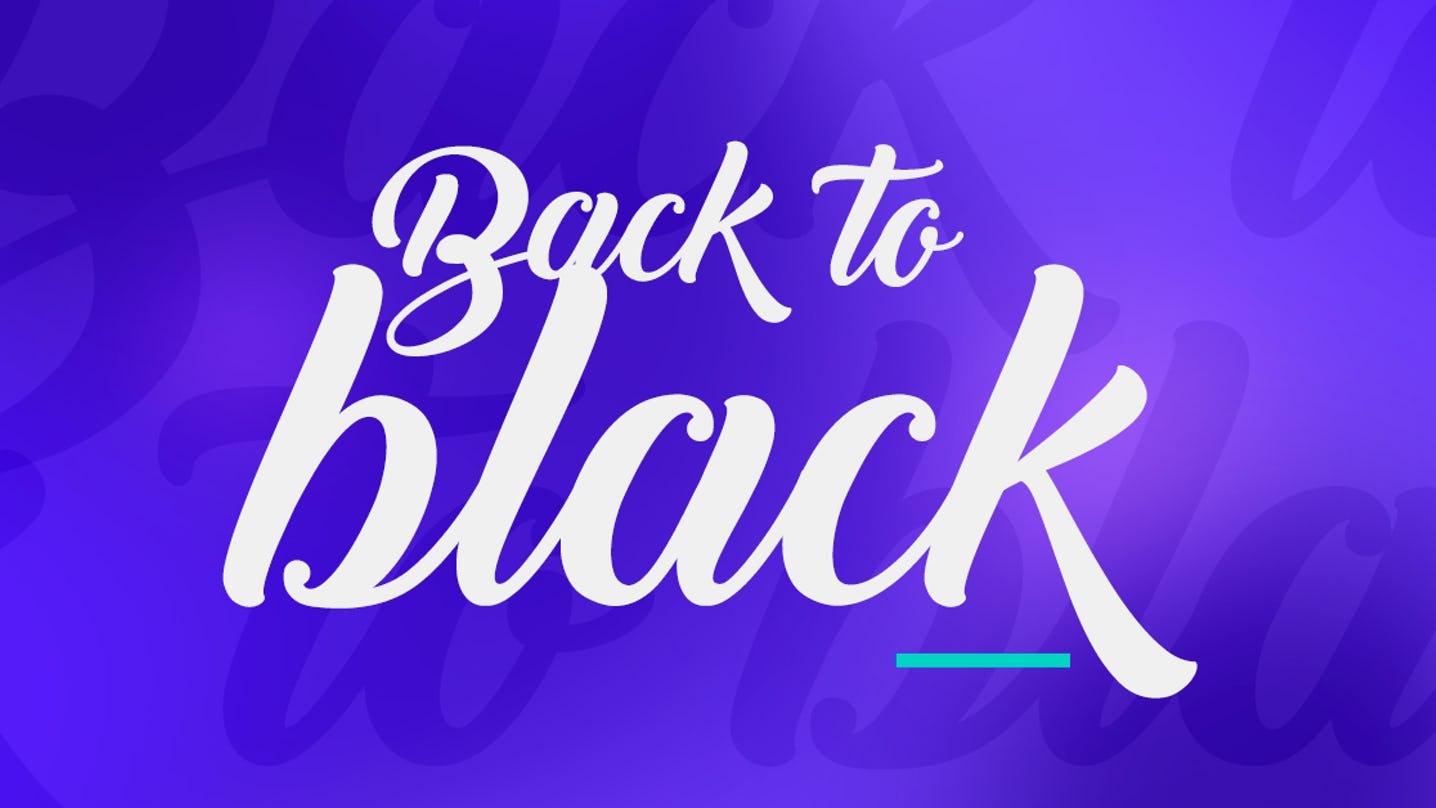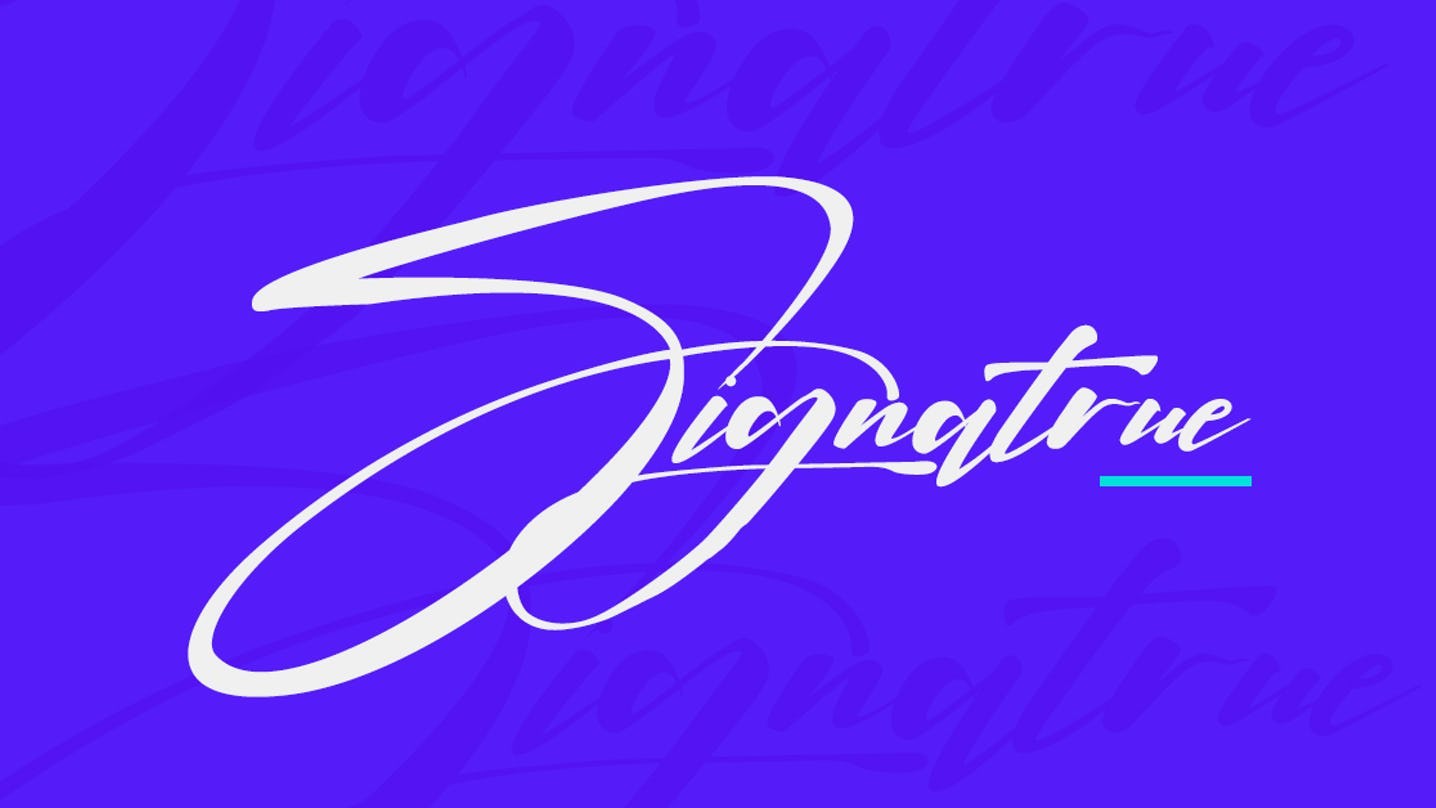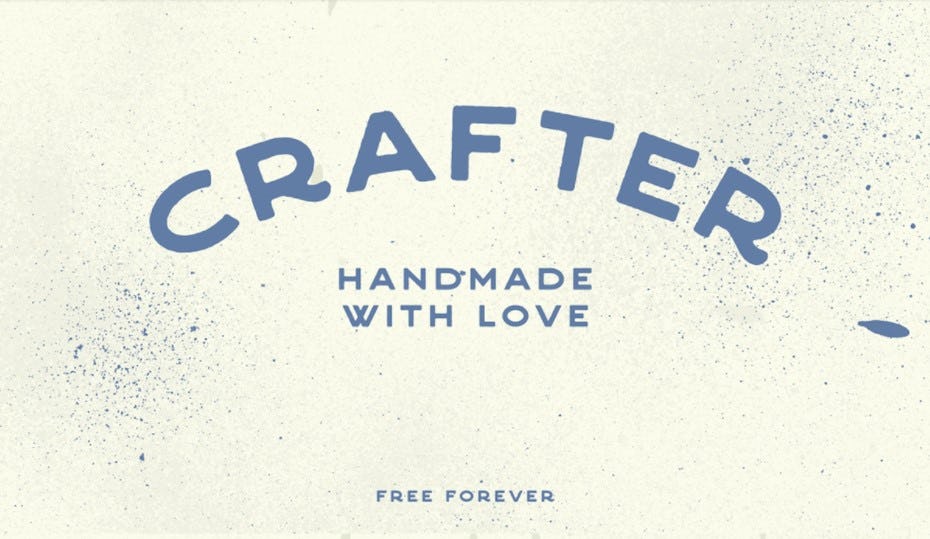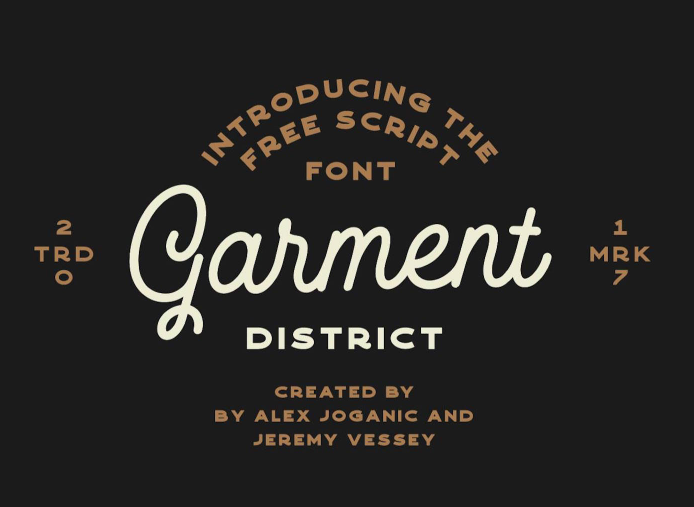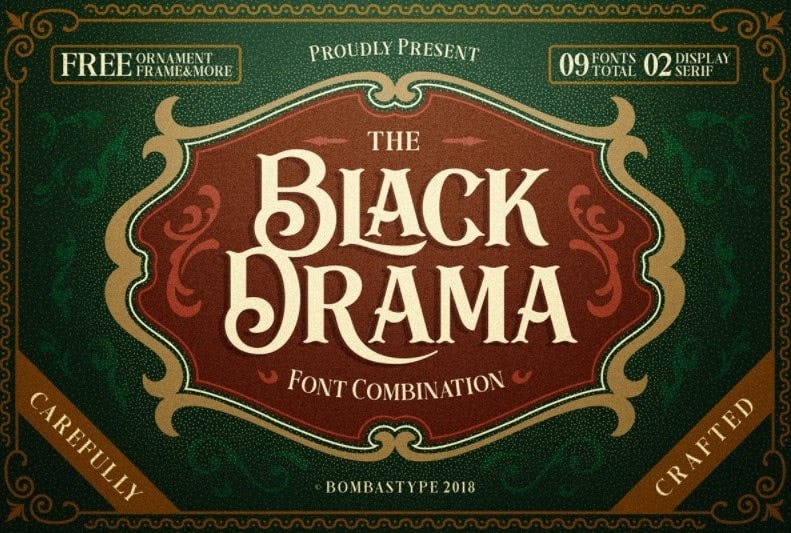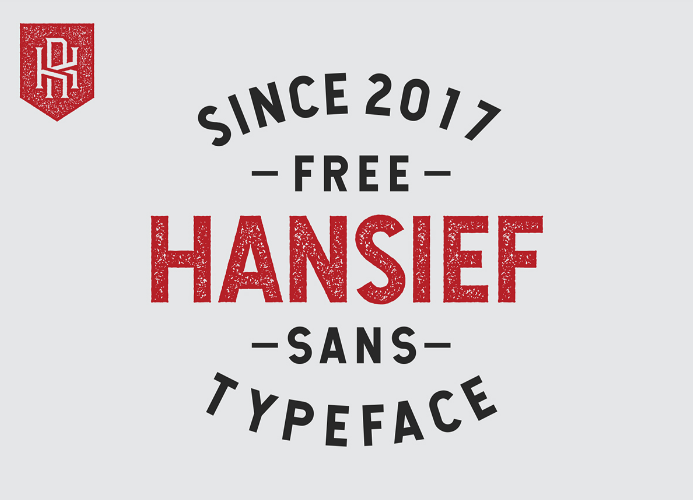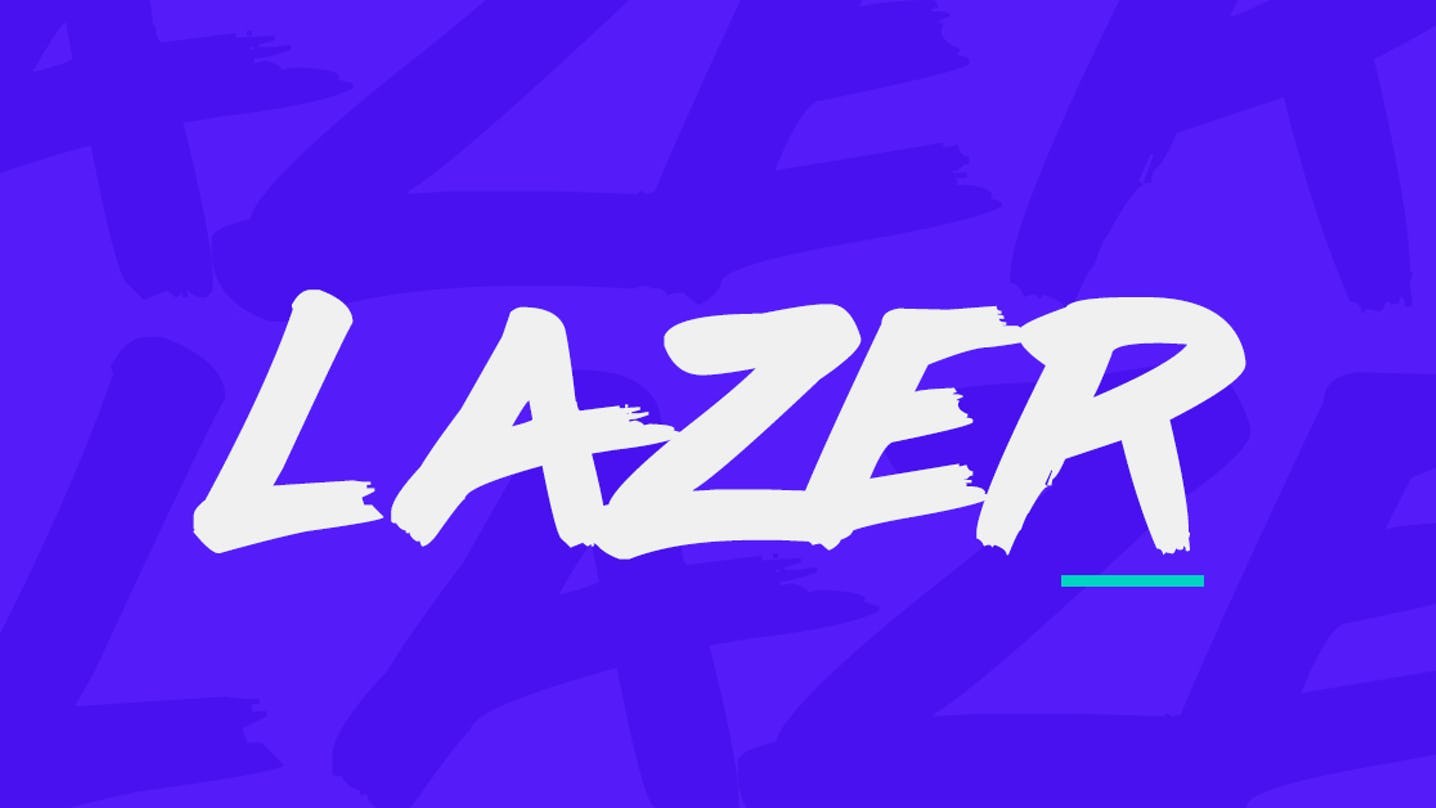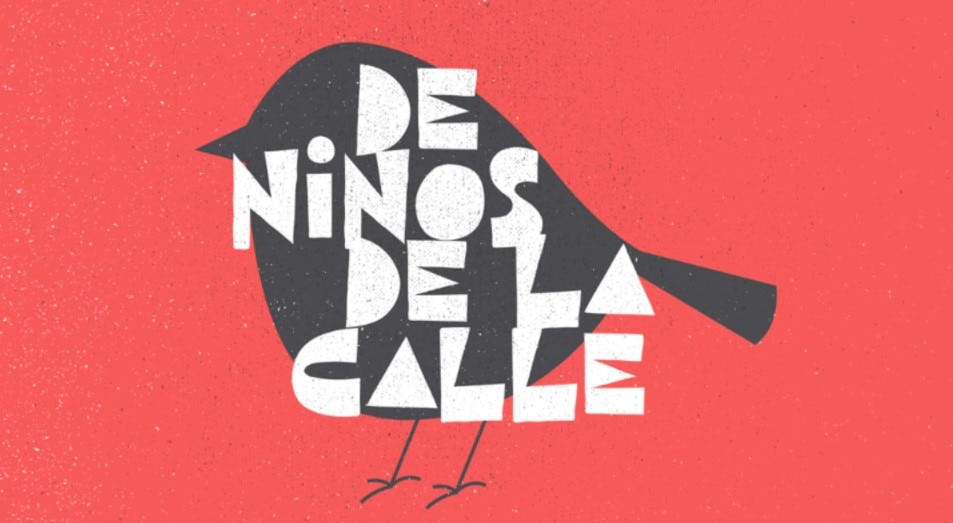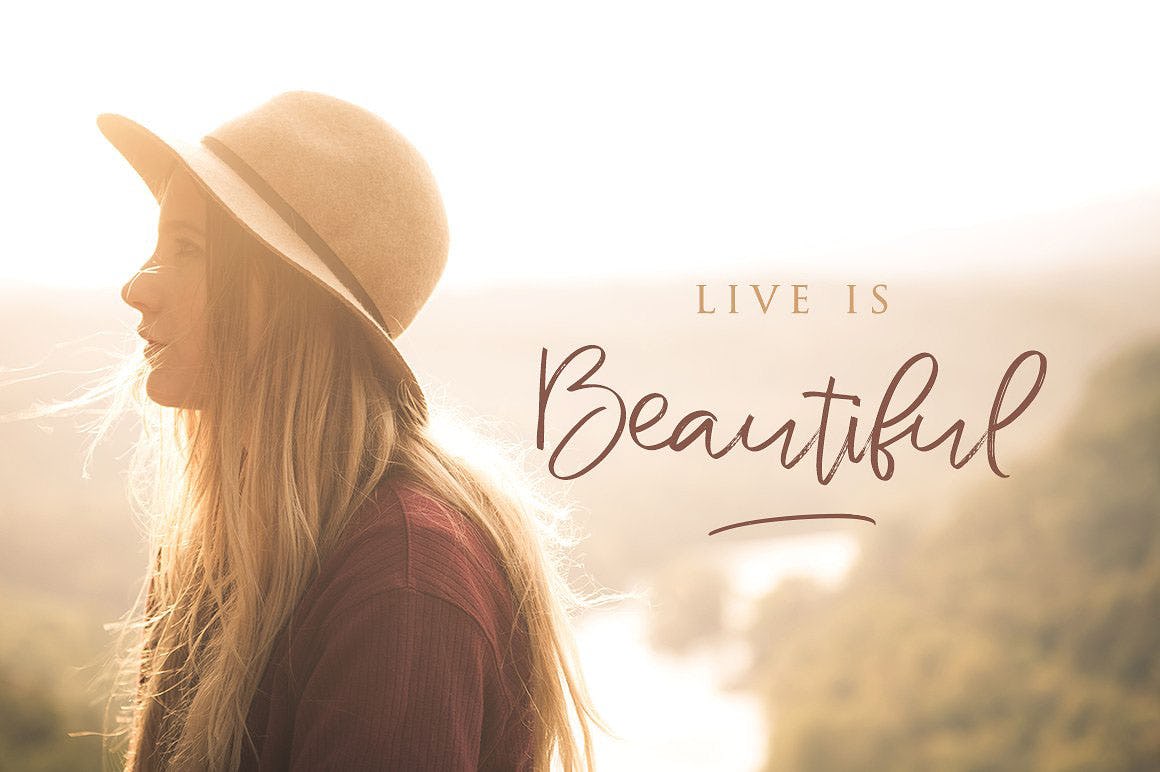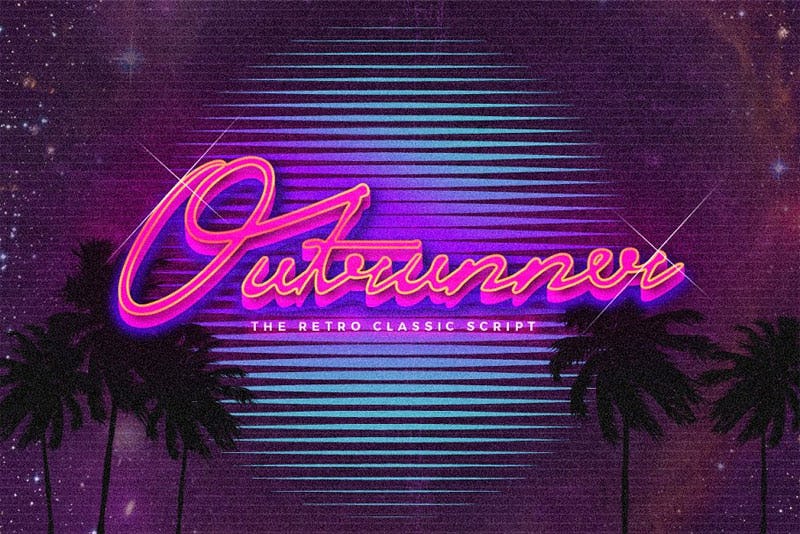
Conhecer o mundo das tipografias vintage é necessário para todo designer gráfico. Por que razão? Porque, ao realizar uma tarefa de design, não são apenas os objetos gráficos e visuais que importam, mas também o formato dos textos que os acompanham. O objetivo é que o espectador que entra em contato com sua peça de design entenda a mensagem que você deseja comunicar num relance. Assim, as tipografias vintage permitem que você gere uma impressão retro na mente do público, comunicando uma mensagem precisa.
Mas quais são as principais tipografias vintage? A que períodos eles se referem? Como podem ser combinados? Não se preocupe, porque em todo este post de Crehana, nós lhe forneceremos um guia informativo completo sobre quais são as melhores tipografias vintage. E como resultado, você terá um ás de estilo vintage na manga como designer profissional.
Streetwear Free Font
Artimasa compartilha conosco a fonte Streetwear, uma fonte vintage e elegante, inspirada na moda e nos esportes dos anos 60 e 70. Esta " velha confiável " é única e divertida ao mesmo tempo, e perfeita para textos, logotipos e frases criativas.
The Night Watch Font
Procurando letras vintage para um projeto com toques clássicos ou medievais? The Night Watch Font é uma fonte vintage gratuita que ajudará você a consolidar os dois estilos. Você pode até usá-lo para evocar o mistério ou para um tema de terror.
Esta é uma fonte retro não convencional com serifs modificados, que chamará a atenção de qualquer material. Utilize-a em ilustrações, cartazes, etc.
Blackletter Font
Se o estilo gótico é o seu estilo, Blackletter Font é o tipo de letra vintage para você. Por ser bold, curvilíneo e pontiagudo, este tipo de letra não só transmite força e rudeza, mas também causa uma grande impressão.
É um tipo de letra incomum com muita personalidade. A melhor coisa: é grátis.
New York Font
Esta é uma fonte retro muito diferente das anteriores. New York Font é caracterizada por ser uma fonte sóbria e elegante. Certamente Artem Nevsky, seu criador, tinha essas palavras em mente quando a criou.
Use este tipo de letra vintage para evocar profissionalismo, seriedade e dar um toque retro aos seus desenhos.
Elsie Font
Você já viu o filme O Grande Gatsby? Esta tipografia vintage nos lembra este filme e seu estilo art deco, um período que surgiu entre as duas guerras mundiais.
Se você está procurando uma fonte retro gratuita que transmita todo o glamour da década de 1920, Elsie Font é a fonte certa para você. Use-a em convites de casamento, camisetas, capas de cadernos, etc. É uma tipografia vintage legível e versátil, pois tem até quatro estilos diferentes.
Barbaro Font
Barbaro Font, de Iván Nuñez, é uma fonte vintage grátis, diretamente do velho oeste. Esta fonte serif personalizada tem duas versões e é ideal para logotipos, postagens em redes sociais, camisetas, cartazes, etc.
Back to Black Font
Back to Black é uma fonte feita à mão pela Misti's Fonts. É um tipo de letra vintage que é geralmente usada para cartões de visita, logotipos e frases. É uma tipografia vintage gratuita para uso pessoal.
Signature Font
Você quer que sua assinatura ou nome tenha a caligrafia do passado? Então você tem que experimentar esta fonte estilo vintage muito parecida com a caligrafia natural.
Lembre-se de que as tipografias vintage são tipos de letras inspiradas na arte manual da era dourada do design gráfico (quando tudo era feito à mão milimetricamente).
Assim, Signature Font é uma daquelas tipografias vintage perfeitas para logotipos, convites de casamento, posts de redes sociais, cartões e qualquer projeto que seja adepto da caligrafia.
Crafter Vintage Font
Crafter é uma das mais versáteis fontes vintage feitas à mão. Seu estilo é inspirado por antigos letreiros metálicos. Seus criadores recomendam o uso deste tipo de letra em logotipos, camisetas, cartazes, redes sociais ou, literalmente, qualquer outra coisa (exceto parágrafos).
Tradesmith Vintage Font
A fonte Tradesmith é o equilíbrio perfeito entre o vintage e o industrial. Este tipo de letra de vintage tem caracteres quadrados e cantos angulosos. É adequada para combinar com outras fontes para criar marcas autênticas, logotipos e lockups.
Inclui 4 estilos: Regular, Round, Rough & Stamp. Portanto, você tem várias opções de tipografias vintage para seus projetos. E o melhor de tudo é que é uma fonte vintage gratuita.
Você pode usar esta fonte vintage em uma variedade de projetos. Entre eles: logotipos, cartazes, etiquetas, design de embalagens, design tipográfico, roupas e capas de livros.
Outrunner Retro Script
Esta fonte vintage é elaborada pela TSV Creative e definitivamente tem uma vibração dos anos oitenta. É uma das fontes categorizadas como "Vaporwave".
É uma fonte retrô clássica que você pode usar para desenhos com estilo futurista, em logotipos ou camisetas.